30 migliori font architettonici del 2023 (gratuiti e premium)
Pubblicato: 2023-08-07Sei un grafico che cerca di portare i tuoi progetti al livello successivo? Bene, non cercare oltre! In questo post del blog, ci tufferemo nel mondo dei font architettonici ed esploreremo le 30 migliori opzioni disponibili.
Ma potresti chiederti, perché i caratteri architettonici sono importanti e come possono migliorare i miei progetti?
I caratteri architettonici sono specificamente progettati per catturare l'essenza e lo stile dell'architettura, rendendoli la scelta perfetta per qualsiasi progetto di design relativo a edifici, paesaggi o progettazione strutturale.
Questi caratteri presentano spesso linee pulite, forme geometriche ed eleganti lettere che trasudano professionalità e raffinatezza.
Incorporando questi caratteri architettonici nei tuoi progetti, puoi creare un'estetica visivamente sbalorditiva e coesa che impressionerà i tuoi clienti ed eleverà il tuo lavoro a nuovi livelli.
Ora, entriamo nel nocciolo di questo articolo. Abbiamo setacciato il Web per offrirti un elenco accuratamente curato dei 30 migliori font architettonici disponibili.
Sia che tu stia lavorando su un progetto, un sito Web per uno studio di architettura o una brochure per una società immobiliare, ti abbiamo coperto con una vasta selezione di caratteri che soddisfano diversi stili e preferenze di design.
Da audace e moderno a elegante e classico, troverai un carattere che si adatta alle tue esigenze e ti aiuta a comunicare la tua visione architettonica in modo efficace. Quindi tuffiamoci ed esploriamo questi fantastici caratteri che daranno vita ai tuoi progetti!
I migliori font architettonici premium
Stai cercando di portare i tuoi progetti architettonici al livello successivo? Non guardare oltre. In questa sezione, abbiamo curato una raccolta dei migliori font architettonici premium che sono garantiti per elevare i tuoi progetti.
Non perdere l'occasione, esplora questi caratteri e dai un tocco di raffinatezza ai tuoi progetti.
Cormier
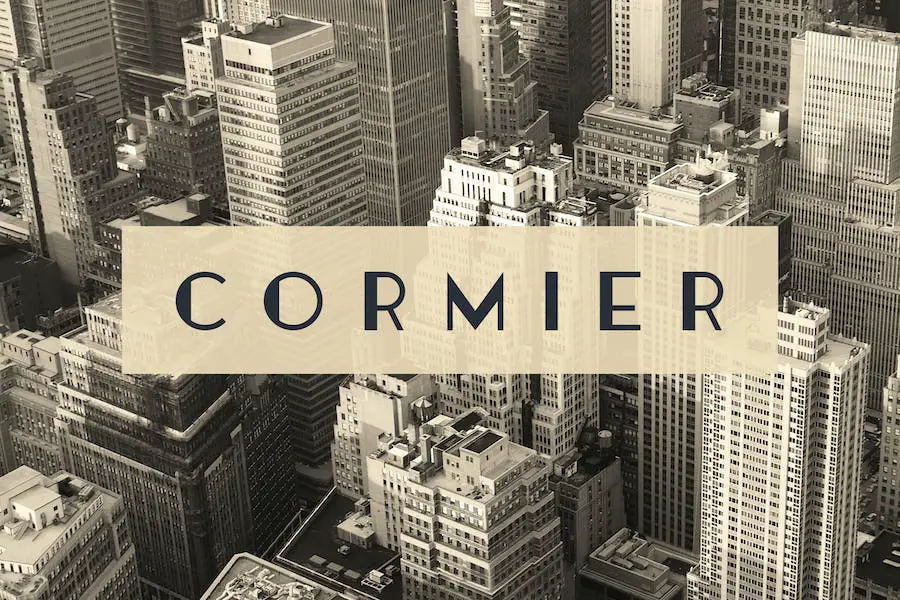
Cormier è un carattere tipografico a tema Art Déco che offre tre stili: ruvido, doppio e regolare. Con lettere maiuscole, numeri e punteggiatura, questo font è perfetto per aggiungere un tocco di eleganza e raffinatezza ai tuoi progetti di graphic design.
Le lettere alternative possono essere facilmente attivate con il blocco maiuscole, consentendo infinite possibilità di creare design unici e accattivanti. Che tu stia lavorando su Google Architectural Fonts o Adobe Architectural Fonts, Cormier eleverà sicuramente i tuoi progetti.
La sua estetica moderna ma senza tempo lo rende versatile per una varietà di applicazioni, tra cui Word, Canva, Circuit e Figma. Inoltre, se stai cercando caratteri architettonici scritti a mano o caratteri calligrafici architettonici, Cormier ti ha coperto con il suo stile elegante e artistico.
Imperiem
Imperiem è un carattere serif semplice ma unico che trae ispirazione dall'architettura e dalle caratteristiche delle antiche civiltà europee. Questo set di caratteri cattura perfettamente l'essenza dell'architettura greca e romana con le sue forti linee verticali diritte che simboleggiano i pilastri portanti di queste civiltà.
Che tu stia lavorando a un progetto per Google, Adobe, Word, Canva, Circuit o Figma, Imperiem è la scelta perfetta per aggiungere un'estetica architettonica moderna al tuo lavoro.
È anche ideale per progetti architettonici, bozze e tipi di portfolio, in quanto fonde perfettamente elementi di design classici con un tocco contemporaneo.
Houston
Houstone è un carattere di visualizzazione Art Déco Sans Serif progettato per elevare i tuoi progetti. Che tu stia lavorando su progetti di branding del logo, design editoriale o industria dei giochi, questo font è perfetto per aggiungere un tocco di raffinatezza.
Con le sue linee pulite e lo stile senza tempo, Houstone è adatto anche per progetti storici e architettonici. Dalla pubblicità moderna alle copertine dei libri, questo carattere versatile farà sicuramente una dichiarazione. Diamo un'occhiata più da vicino agli attributi che rendono Houstone una scelta straordinaria.
Innanzitutto, il design nitido ed elegante di Houstone è ciò che lo distingue. La sua influenza Art Déco aggiunge un tocco di glamour e raffinatezza, rendendolo perfetto per progetti di fascia alta.
Reusco
Reusco è un font che offre una moltitudine di opzioni per migliorare il tuo design tipografico. Con le sue alternative, puoi creare il look perfetto per vari progetti, dai loghi di lusso ai design editoriali e al marchio di boutique.
Che tu stia lavorando a una promozione di moda o a un pezzo di architettura storica, Reusco ti copre.
Questo carattere versatile è ideale anche per articoli di cancelleria, design di blog, pubblicità, inviti e persino decorazioni per la casa. Le possibilità sono infinite con Reusco nel tuo arsenale creativo.